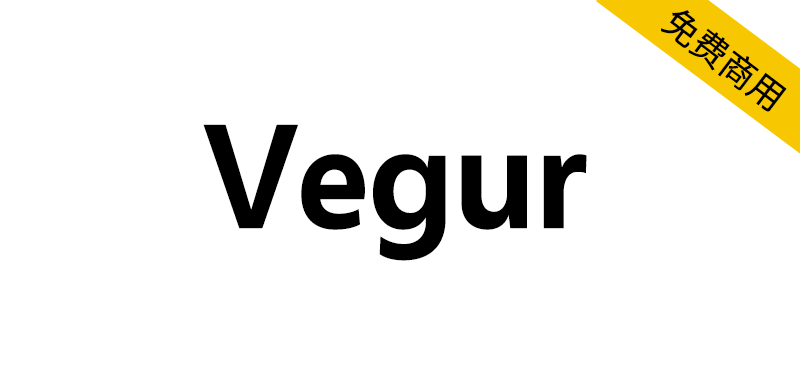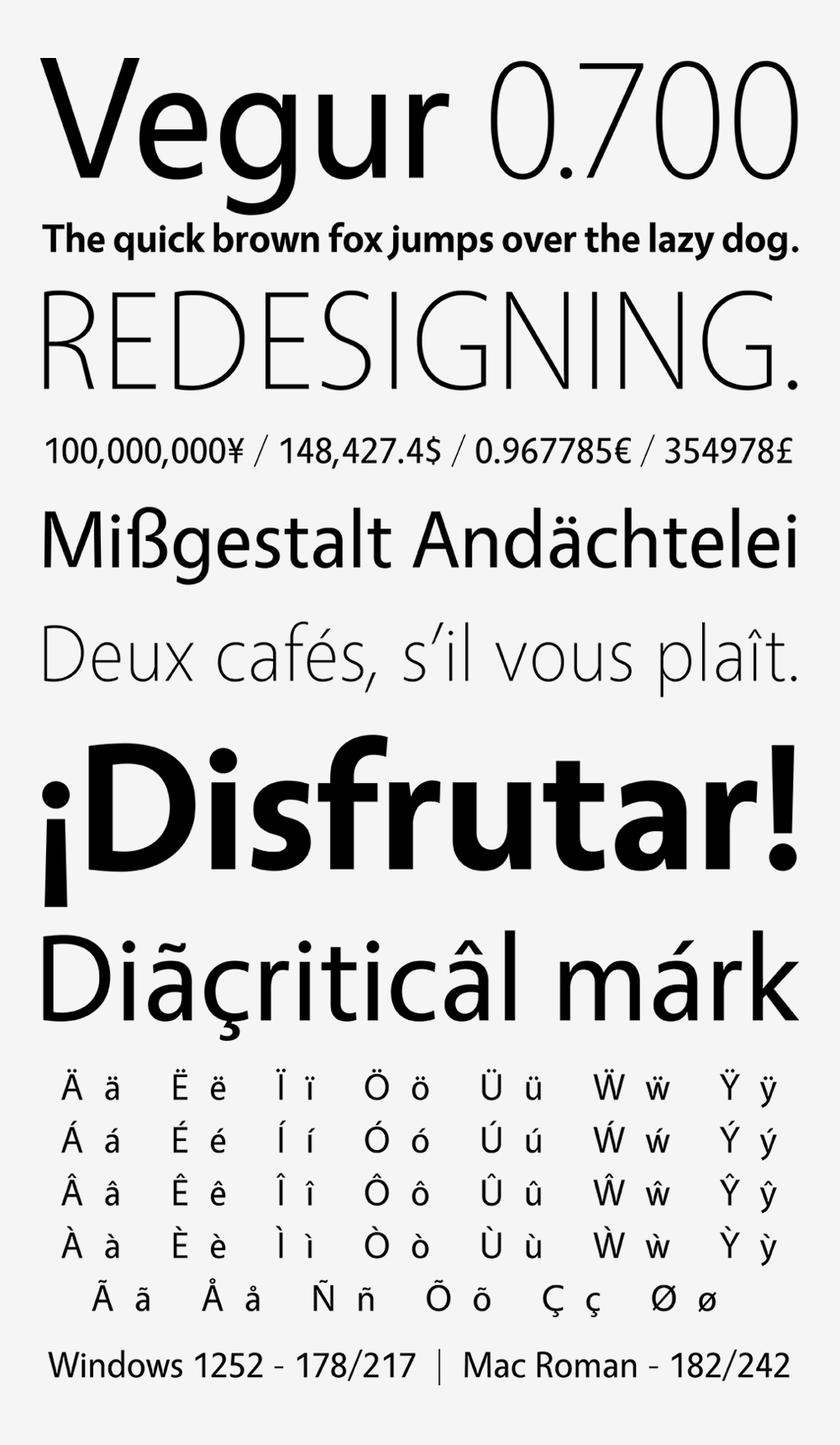
Vegur 是一种人文主义无衬线字体,专为点冒号标识而开发。借着更新0.700版本的机会,我们重新审视了设计,修复了拉伸的部分,以创造出更锐利的印象。它还被调整为比之前的版本更长,整体看起来更干净。特别是,我认为已经推迟的粗体字号的印象通过这次更新有了很大的改变。
此外,我们还添加了大量字符,例如变音符号(添加到字母表中的符号)、连字(例如法语中的 Æ 和 Œ 以及德语中的 ß)。此外,我们还添加了英镑(英镑)和欧元(欧元)等代表性货币符号,以及欧洲国家的标点符号。尽管并非所有字符和符号均可用,但我们计划在未来的更新中添加更多字符和符号。
Vegurはdot colonのロゴタイプ用に開発されたヒューマニストサンセリフフォントです。0.700バージョンへのアップデートを機にデザインを一から見直し、間延びしていた部分を整えシャープな印象に仕上げました。 また、以前のバージョンよりも長体気味に調整し、全体としてすっきりした印象になるようにしています。 特に間延びしていたBoldウェイトも今回のアップデートで大きく印象が変わったと思います。
そのほか、ダイアクリティカルマーク(アルファベットに付される記号)やフランス語のÆやŒといった合字、ドイツ語のßなどの文字を大幅に追加しました。 さらに、£(スターリング・ポンド)・€(ユーロ)といった代表的な通貨記号や欧州圏の約物記号も追加しました。 まだすべての文字・記号が揃っている訳ではありませんが、今後のアップデートで順次追加していく予定です。